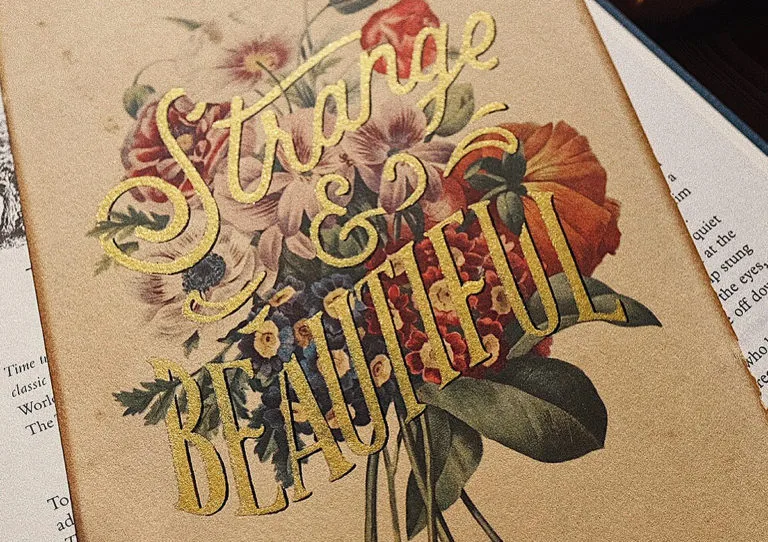
Letras criativas e estilosas criadas por Travis Stewart
O ilustrador e designer Travis Stewart criou uma série de tipografias modernas e criativas feitas à mão.
Suas letras são impressionantes e criativas e nem parece que foram produzidas sem a ajuda de programas. Além de usar suas criações em seus projetos, o designer ainda vende suas tipografias.